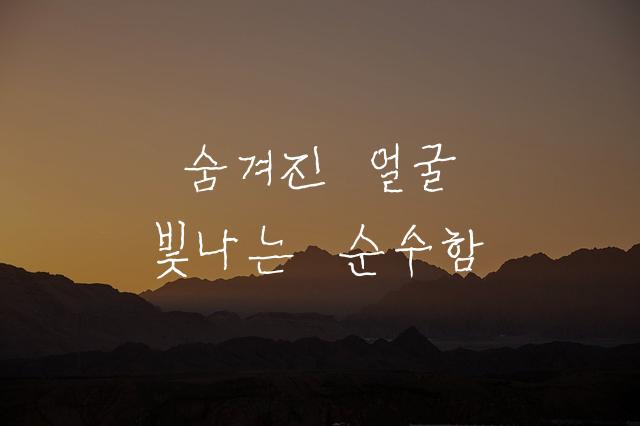
그녀-이옥선 폰트는 나비레터에서 제작한 다소 삐뚤빼뚤하고 마카 느낌의 감성이 풍부한 폰트입니다. 이 특유의 스타일은 독특하고 개성 넘치는 디자인을 가능하게 합니다.
그녀-이옥선은(는)
펜/붓터치 계열의 생김새를 가지고 있으며
초대장, 일기/편지 등에서 자주 활용되며, 효과적인 메시지 전달에 적합합니다.
이 폰트는 라이프스타일, 문화/예술 분야에 잘 어울리며,
감성적인, 예술적인 느낌을 담고 있는 것이 특징입니다.